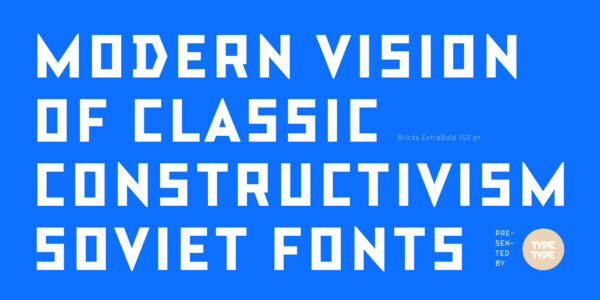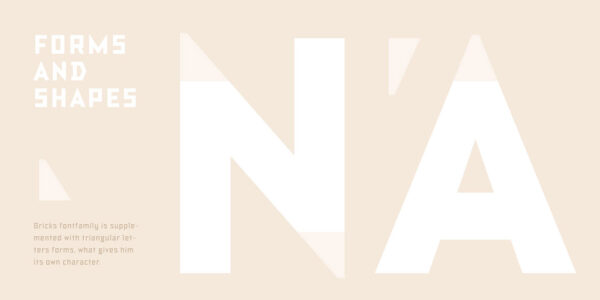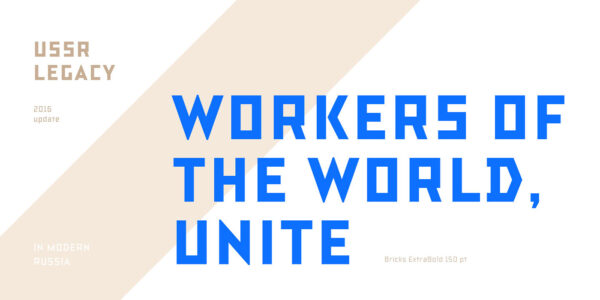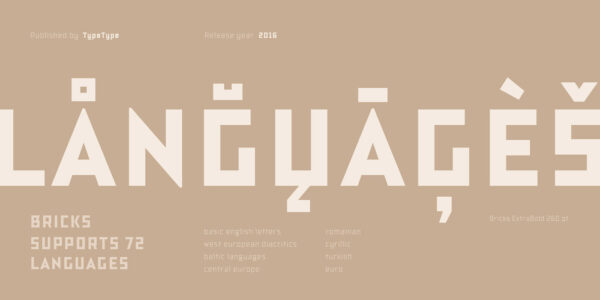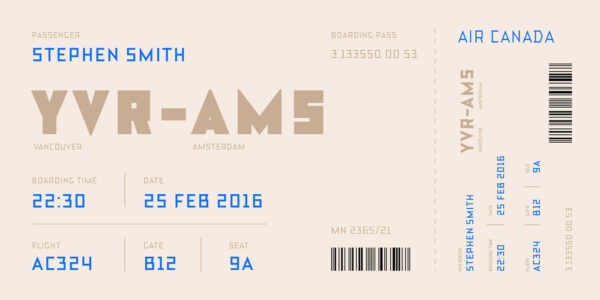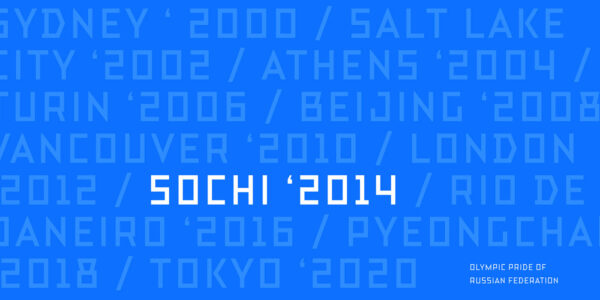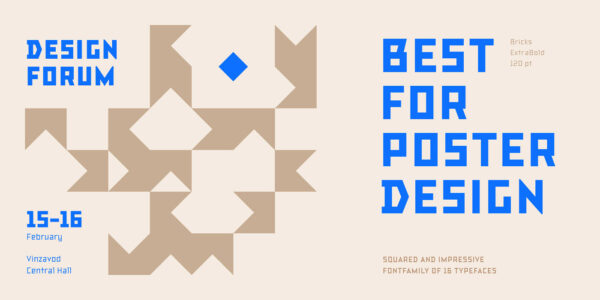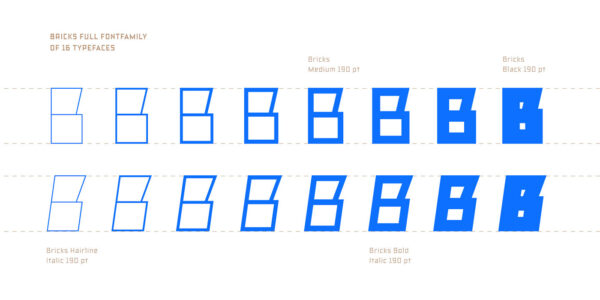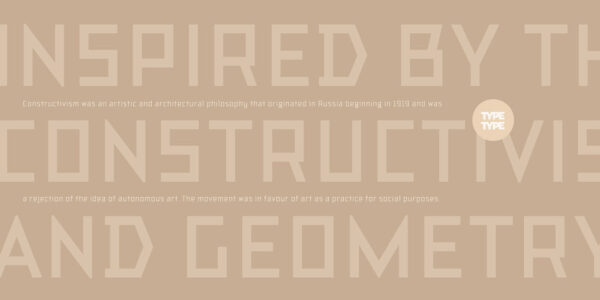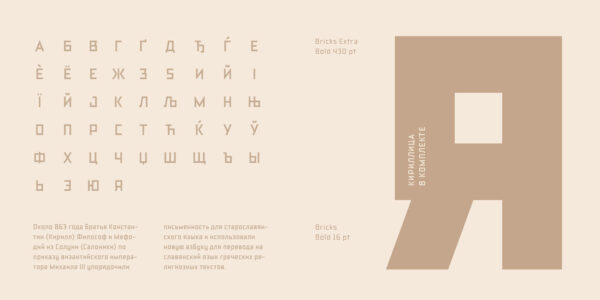
TT Bricks
TT Bricks — ТТ Брикс
Произносится «ТТ Брикс». «Bricks» — производное слово от brick, в переводе с английского «кирпич». Буквы «TT» являются аббревиатурой названия компании.
TT Bricks — шрифт, вдохновлённый ранней советской визуальной культурой и эпохой конструктивизма.
Cвежее и визуально мощное шрифтовое семейство
Любите ли вы раннюю советскую визуальную культуру как любим её мы? Мы попытались вернуться обратно на 100 лет назад и переосмыслить эпоху конструктивизма. Мы создали очень большую шрифтовую гарнитуру, которая состоит из самых простых квадратных и трегольных форм. Шрифтовое семейство TT Bricks имеет 16 начертаний: Hairline, Thin, Light, Regular, Medium, Bold, ExtraBold, Black и Italics.
Благодаря простым формам всех знаков, TT Bricks идеально выглядит в очень маленьких размерах
Отлично вписывается в современное пространство медиа
О гарнитуре TT Bricks
Любите ли вы раннюю советскую визуальную культуру как любим её мы? Мы попытались вернуться обратно на 100 лет назад и переосмыслить эпоху конструктивизма. Мы создали очень большую шрифтовую гарнитуру, которая состоит из самых простых квадратных и трегольных форм. Шрифтовое семейство TT Bricks имеет 16 начертаний: Hairline, Thin, Light, Regular, Medium, Bold, ExtraBold, Black и Italics.
Несмотря на свое советское прошлое, TT Bricks выглядит очень свежим и визуально мощным шрифтовым семейством, которое отлично вписывается в современное медиапространство. TT Bricks отлично подходит для мобильных приложений и корпоративных сайтов, а также для верстки периодических изданий. Благодаря гипертрофированно простым формам всех знаков, TT Bricks идеально выглядит в очень маленьких размерах.